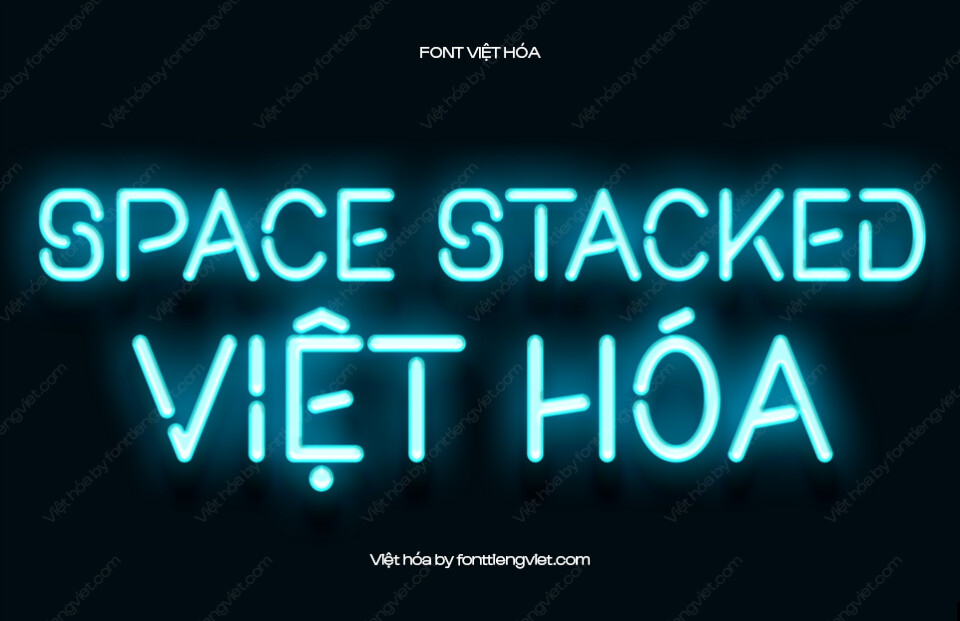
Font Việt hóa 1FTV VIP Space Stacked – Kiểu Neon
Giới thiệu về Font Việt hóa 1FTV VIP Space Stacked – Kiểu Neon
Trong thế giới đồ họa hiện đại, việc lựa chọn một bộ Font Miễn Phí chất lượng luôn là ưu tiên hàng đầu của các bạn học sinh và giáo viên khi làm bài thuyết trình hay báo tường. Font Việt hóa 1FTV VIP Space Stacked – Kiểu Neon nổi bật như một giải pháp hoàn hảo mang phong cách tương lai và đậm chất nghệ thuật ánh sáng. Bộ font này được thiết kế với các đường nét xếp chồng độc đáo, tạo nên hiệu ứng thị giác mạnh mẽ như những bảng hiệu đèn neon rực rỡ trên đường phố về đêm. Đặc biệt, phiên bản này đã được Việt hóa hoàn chỉnh, giúp người dùng dễ dàng sử dụng các ký tự tiếng Việt có dấu mà không lo bị lỗi hiển thị hay mất nét.
Ưu điểm nổi bật của Font Việt hóa 1FTV VIP Space Stacked – Kiểu Neon
Thiết kế hiện đại và linh hoạt
Bộ Font Việt hóa 1FTV VIP Space Stacked – Kiểu Neon mang đến hơi thở của kỷ nguyên số và không gian vũ trụ. Cấu trúc chữ cái được chăm chút kỹ lưỡng, phù hợp cho các tiêu đề lớn, banner sự kiện hoặc các dự án sáng tạo cần sự phá cách. Đối với môi trường học đường, giáo viên có thể dùng font này để làm nổi bật các đề mục chính trong bài giảng điện tử, giúp học sinh hứng thú hơn với bài học. Kiểu dáng xếp chồng (stacked) tạo độ dày và chiều sâu, giúp nội dung trở nên sống động hơn trên màn hình hoặc khi in ấn.
Khả năng ứng dụng đa dạng
Không chỉ dừng lại ở các thiết kế công nghệ, font chữ này còn rất phù hợp cho các video ngắn trên mạng xã hội hoặc làm thumbnail cho kênh học tập. Sự kết hợp giữa kiểu dáng Neon và bảng mã tiếng Việt chuẩn giúp người dùng tự do sáng tạo nội dung mà vẫn đảm bảo tính thẩm mỹ cao nhất.
Kết luận về bộ font độc đáo
Việc sử dụng Font Việt hóa 1FTV VIP Space Stacked – Kiểu Neon sẽ giúp dự án của bạn trở nên chuyên nghiệp và ấn tượng hơn bao giờ hết. Đây là lựa chọn tuyệt vời cho bất kỳ ai đang tìm kiếm sự mới mẻ trong thiết kế đồ họa tiếng Việt. Hãy truy cập ngay trang Font Miễn Phí, Font Việt Hóa, Font Việt hóa 1FTV VIP Space Stacked – Kiểu Neon để tải về và trải nghiệm sức mạnh của bộ font độc đáo này nhé.